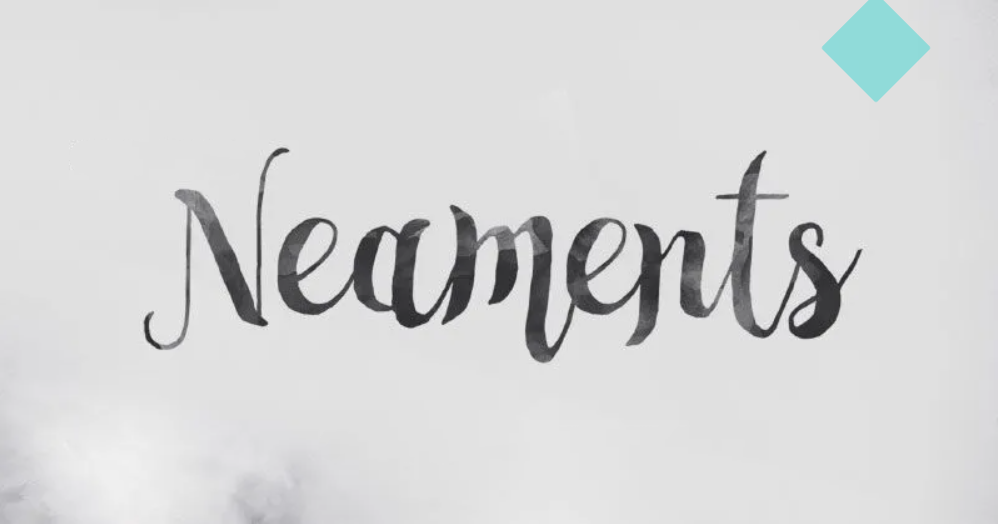
Neament Font có sẵn dưới dạng phông chữ Personal & Commercial Use được trang bị bắt đầu từ chữ hoa, chữ thường, Số và một số ký tự đặc biệt và thay thế.
Neament Font rất phù hợp cho logo, nhãn hiệu, lời mời, văn phòng phẩm, thiết kế đám cưới, lời mời, logo, danh thiếp, bìa, trên áo sơ mi, bài đăng trên phương tiện truyền thông xã hội và hơn thế nữa. Nó cũng sẽ được sử dụng để tạo ra một hình ảnh, văn bản tuyệt vời với nhiều loại màu sắc và văn bản.